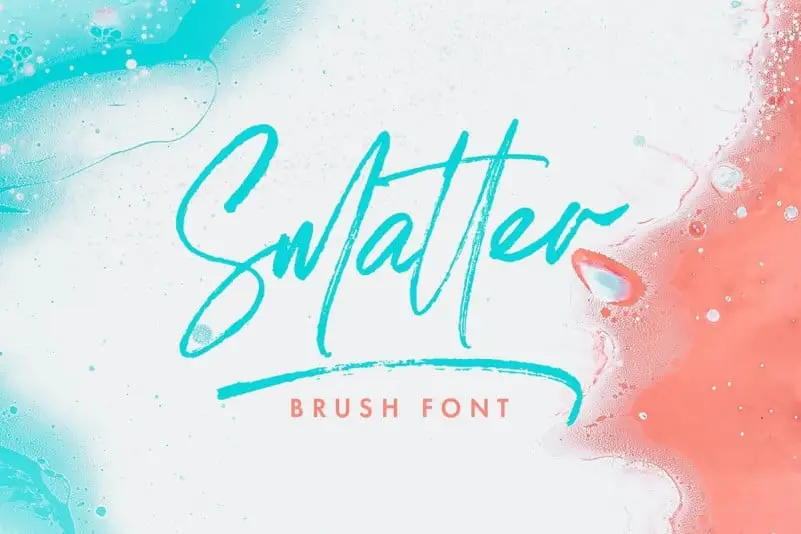
Smatter Brush Font – Download Grátis
A Smatter Brush Font é uma elegante fonte de tração assinatura criada pelo Surplus Type Co., oferecendo características que permitem combinações surpreendentes. Esta fonte foi desenvolvida para designers e grafistas, especialmente aqueles procurando por algo que possa dar um toque único aos seus trabalhos. Com um amplo leque de ligações, alternativas e swashes, a Smatter Brush Font permite à criatividade fluir livremente, facilitando o processo de criação de designs gráficos personalizados. Perfeita para ambientes como assinaturas de marca, citações, redes sociais, anúncios, embalagens, materiais promocionais e muito mais, a Smatter Brush Font é uma escolha ideal para aqueles que buscam estilos únicos e criativos em suas criações gráficas.